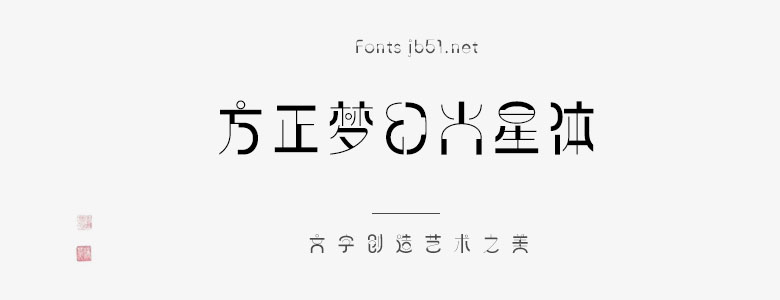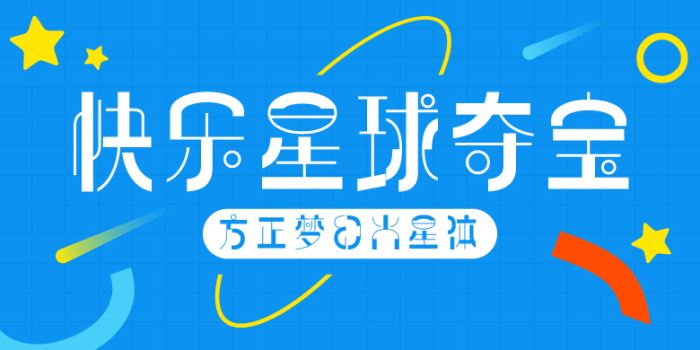
方正夢幻火星體由方正字庫楊悸,郭炳權(quán)設(shè)計師出品的藝術(shù)字體,字體整個構(gòu)思是以圓形為主導(dǎo)的設(shè)計基礎(chǔ),有時全圓、半邊圓、缺圓等不規(guī)則的圓形在設(shè)計中屢屢出現(xiàn),利用與圓有關(guān)的美妙線條運行,以表達(dá)火星變幻莫測的形態(tài),是人類夢想追求的字體,適合應(yīng)用于藝術(shù)設(shè)計、平面宣傳設(shè)計、網(wǎng)頁設(shè)計,書法等領(lǐng)域。
我國航天科研進(jìn)步,有目共睹,已超越了世界水平,人類未來的幻想都有機(jī)會踏足地球以外的世界,星球里存在許多不明因素,讓人類不停地去探索,充滿幻想和變化的星球,鼓動著郭炳權(quán)老師研發(fā)了這一款“夢幻火星體”,郭老師帶領(lǐng)團(tuán)隊在2020年開始做設(shè)計準(zhǔn)備,待“祝融號”成功登陸火星后,即全速進(jìn)行,“夢幻火星體”整個構(gòu)思是以圓形為主導(dǎo)的設(shè)計基礎(chǔ),有時全圓、半邊圓、缺圓等不規(guī)則的圓形在設(shè)計中屢屢出現(xiàn),利用與圓有關(guān)的美妙線條運行,以表達(dá)火星變幻莫測的形態(tài),是人類夢想追求的字體,郭老師盡量把想象不到的形態(tài)充分發(fā)揮出來,充滿夢幻時代感,“夢幻火星體”是創(chuàng)新的未來字體,每個部件都巧妙地搭配,所以難度十足,中國字體市場也是第一次出現(xiàn),團(tuán)隊精心構(gòu)思和鉆研,配合年青人超級想象力,適合創(chuàng)新男女品牌、手機(jī)、電腦產(chǎn)品、科研產(chǎn)品、新能源、汽車品牌、科學(xué)書籍、年青人飲料、運動鞋、體育用品等高科技行業(yè)宣傳和包裝。。